Font chữ cho ebook, lead magnet và tài liệu PDF bán hàng
Gợi ý 15 font TH Việt hóa cho ebook, lead magnet, workbook, checklist PDF và tài liệu bán hàng chuyên nghiệp.
Ebook, lead magnet và tài liệu PDF bán hàng không giống banner quảng cáo. Người đọc có thể dành vài phút đến vài chục phút để xem nội dung, nên font cần vừa đẹp vừa bền mắt. Một font quá trang trí có thể làm bìa nổi bật, nhưng khi đưa vào heading dài, checklist, workbook hoặc đoạn giải thích, tài liệu sẽ nhanh mệt và thiếu chuyên nghiệp.
Bài viết này gợi ý 15 font TH Việt hóa phù hợp để làm ebook, mini guide, checklist PDF, workbook, tài liệu khóa học, proposal và PDF bán hàng. Danh sách ưu tiên các font serif thanh lịch, sans-serif hiện đại và một vài font sang trọng dùng cho điểm nhấn. Mục tiêu là giúp anh chọn font theo vai trò rõ ràng: bìa, heading, body, bảng biểu, CTA và trang testimonial.
Chọn font cho ebook và PDF cần chú ý gì?
Điểm quan trọng nhất là khả năng đọc. Tài liệu PDF thường có nhiều đoạn chữ, bullet, khung ghi chú, bảng checklist và phần điền thông tin. Vì vậy, anh nên dùng font cá tính ở bìa hoặc heading, còn phần thân bài nên chọn font gọn, rõ dấu tiếng Việt và có nhịp chữ ổn. Nếu tài liệu dùng để bán hàng, font còn cần tạo cảm giác đáng tin: không quá trẻ con, không quá rối, không làm giảm giá trị cảm nhận của offer.
Top 15 font TH cho ebook, lead magnet và tài liệu PDF
1. TH Waking - bìa ebook, heading chương và tài liệu tư vấn cao cấp
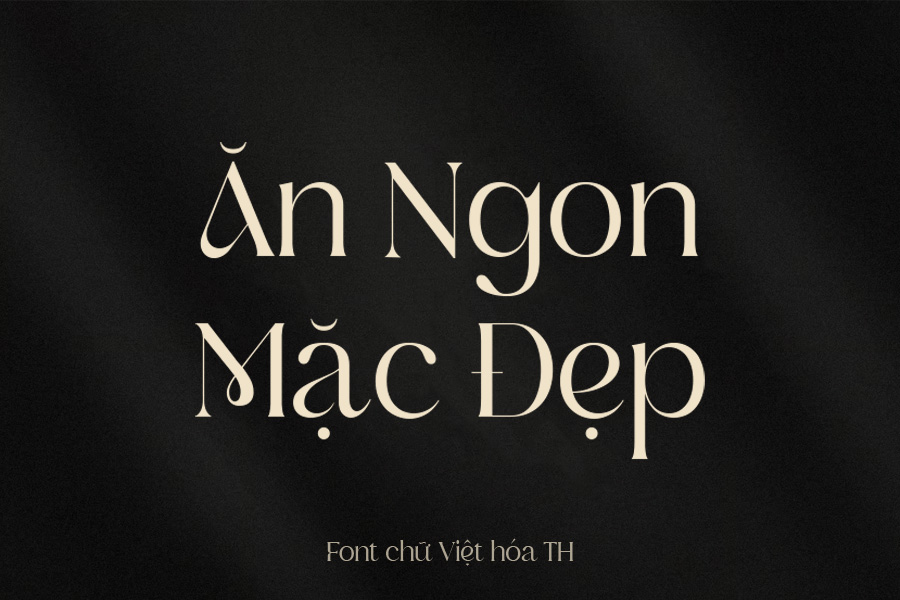
Tải font TH Waking nếu anh đang thiết kế bìa ebook, heading chương và tài liệu tư vấn cao cấp. Điểm mạnh của TH Waking là serif hiện đại, tạo cảm giác đáng tin và có chiều sâu ngay từ trang bìa. Với ebook hoặc lead magnet, font này nên được thử trên cả trang bìa và một trang nội dung mẫu để xem dấu tiếng Việt, khoảng cách dòng và độ rõ của bullet.
Khi dùng trong PDF bán hàng, anh nên xác định vai trò trước: font nào dành cho tiêu đề lớn, font nào dành cho heading phụ, font nào dùng cho đoạn mô tả. Nếu dùng TH Waking cho cover, phần body nên đi với một sans-serif sạch để tài liệu không bị nặng mắt.
2. TH Marlino - ebook chuyên môn, whitepaper, guide dài và báo cáo PDF
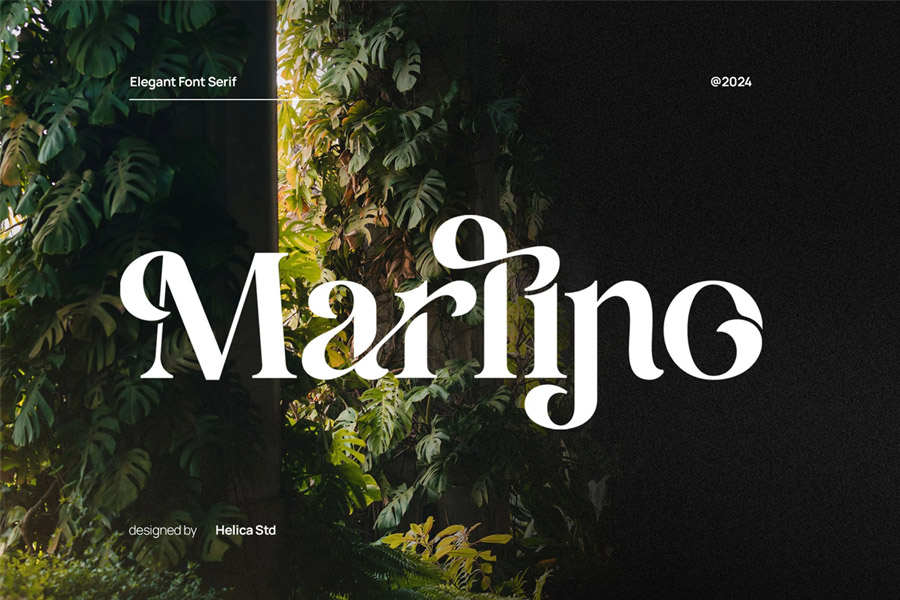
Tải font TH Marlino nếu anh đang thiết kế ebook chuyên môn, whitepaper, guide dài và báo cáo PDF. Điểm mạnh của TH Marlino là chữ có chân rõ ràng, phù hợp với nội dung cần giọng điệu nghiêm túc. Với ebook hoặc lead magnet, font này nên được thử trên cả trang bìa và một trang nội dung mẫu để xem dấu tiếng Việt, khoảng cách dòng và độ rõ của bullet.
Khi dùng trong PDF bán hàng, anh nên xác định vai trò trước: font nào dành cho tiêu đề lớn, font nào dành cho heading phụ, font nào dùng cho đoạn mô tả. Nếu dùng TH Marlino cho cover, phần body nên đi với một sans-serif sạch để tài liệu không bị nặng mắt.
3. TH Runsling - lead magnet cho coach, consultant, beauty, lifestyle và dịch vụ premium
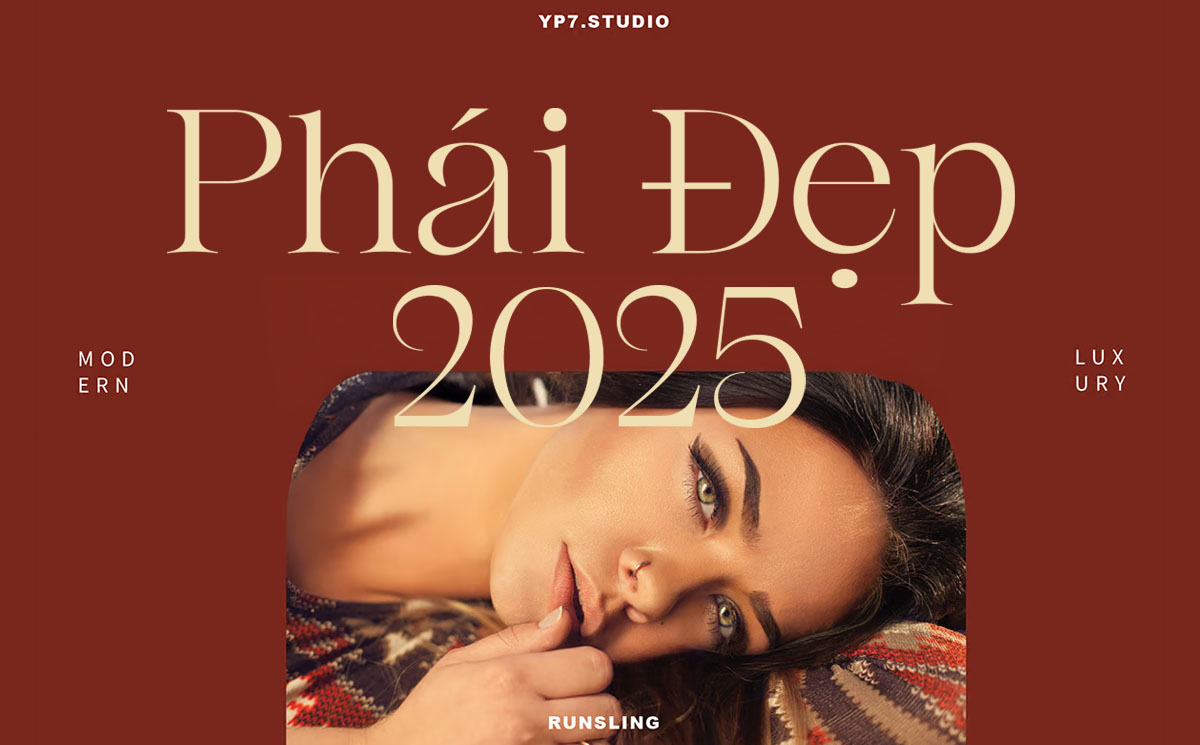
Tải font TH Runsling nếu anh đang thiết kế lead magnet cho coach, consultant, beauty, lifestyle và dịch vụ premium. Điểm mạnh của TH Runsling là thanh lịch, hiện đại, hợp với tài liệu bán hàng không muốn quá cứng. Với ebook hoặc lead magnet, font này nên được thử trên cả trang bìa và một trang nội dung mẫu để xem dấu tiếng Việt, khoảng cách dòng và độ rõ của bullet.
Khi dùng trong PDF bán hàng, anh nên xác định vai trò trước: font nào dành cho tiêu đề lớn, font nào dành cho heading phụ, font nào dùng cho đoạn mô tả. Nếu dùng TH Runsling cho cover, phần body nên đi với một sans-serif sạch để tài liệu không bị nặng mắt.
4. TH Vadola - cover checklist, workbook thẩm mỹ và headline trang mở đầu
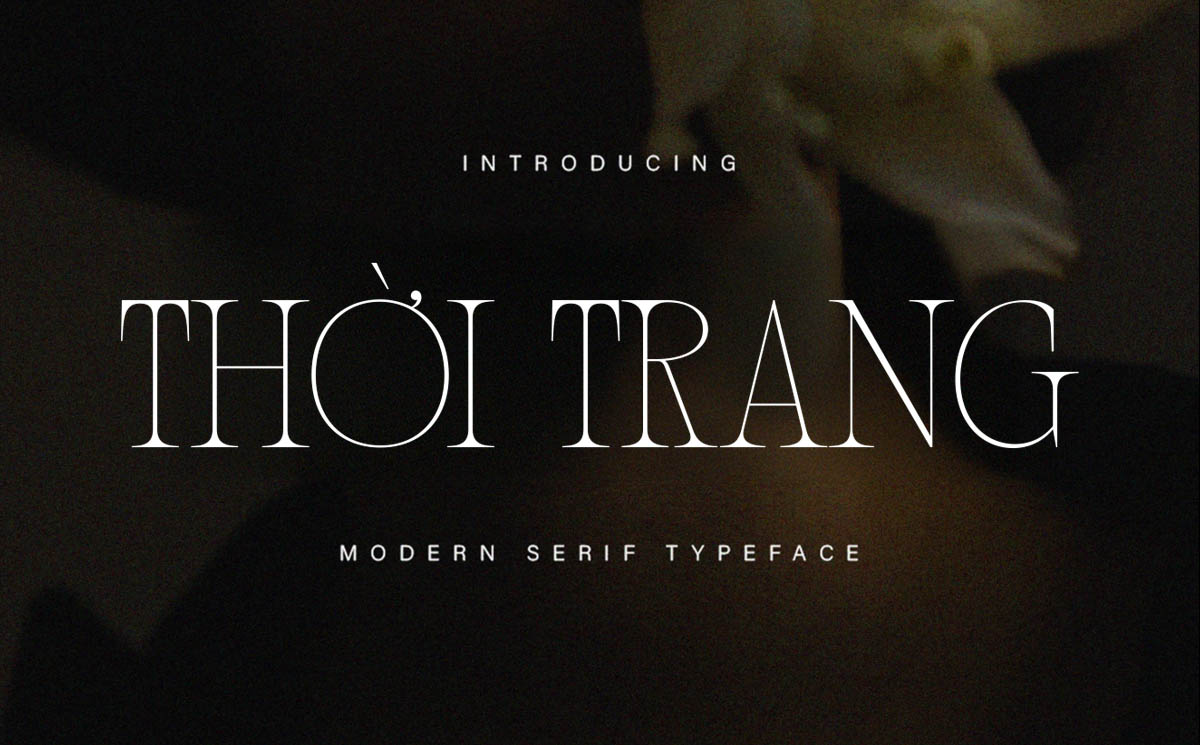
Tải font TH Vadola nếu anh đang thiết kế cover checklist, workbook thẩm mỹ và headline trang mở đầu. Điểm mạnh của TH Vadola là nét mảnh tạo cảm giác nhẹ, tinh tế, đẹp khi đi cùng nhiều khoảng trắng. Với ebook hoặc lead magnet, font này nên được thử trên cả trang bìa và một trang nội dung mẫu để xem dấu tiếng Việt, khoảng cách dòng và độ rõ của bullet.
Khi dùng trong PDF bán hàng, anh nên xác định vai trò trước: font nào dành cho tiêu đề lớn, font nào dành cho heading phụ, font nào dùng cho đoạn mô tả. Nếu dùng TH Vadola cho cover, phần body nên đi với một sans-serif sạch để tài liệu không bị nặng mắt.
5. TH Luxury 2 - ebook thương hiệu cá nhân, tài liệu khóa học và mini guide cao cấp
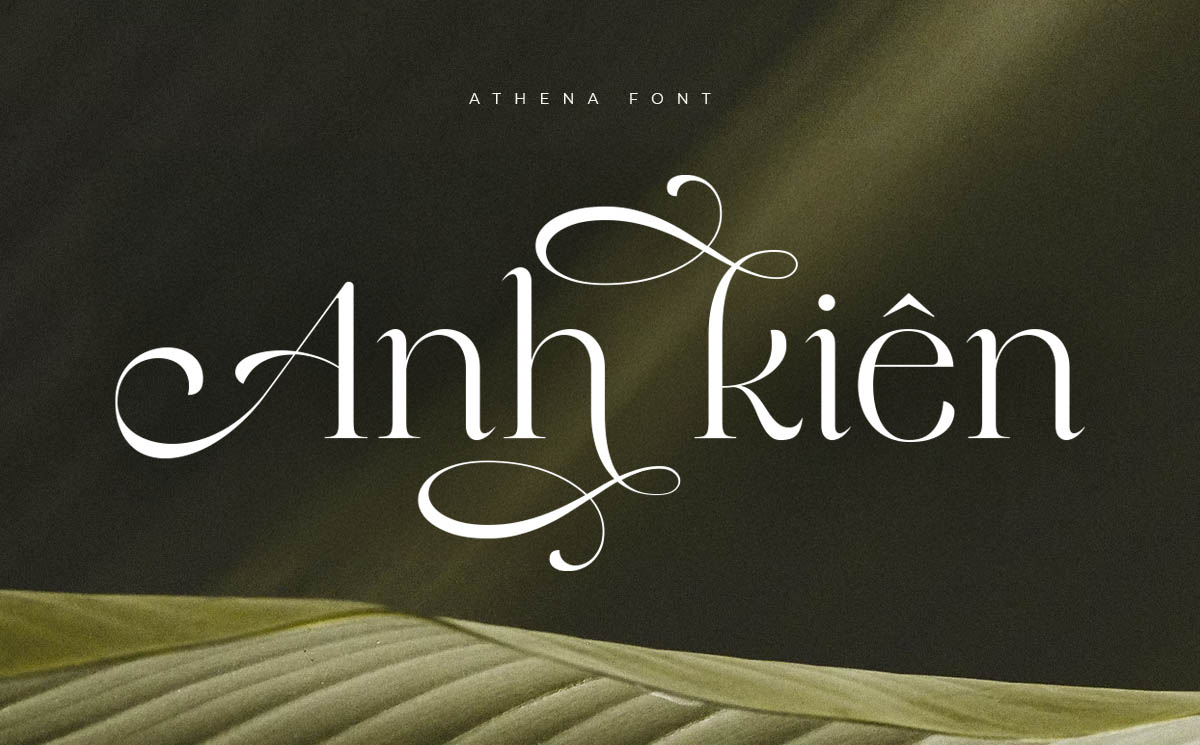
Tải font TH Luxury 2 nếu anh đang thiết kế ebook thương hiệu cá nhân, tài liệu khóa học và mini guide cao cấp. Điểm mạnh của TH Luxury 2 là serif thanh lịch, giúp title nhìn có giá trị hơn khi dùng trên bìa PDF. Với ebook hoặc lead magnet, font này nên được thử trên cả trang bìa và một trang nội dung mẫu để xem dấu tiếng Việt, khoảng cách dòng và độ rõ của bullet.
Khi dùng trong PDF bán hàng, anh nên xác định vai trò trước: font nào dành cho tiêu đề lớn, font nào dành cho heading phụ, font nào dùng cho đoạn mô tả. Nếu dùng TH Luxury 2 cho cover, phần body nên đi với một sans-serif sạch để tài liệu không bị nặng mắt.
6. TH Luxury 5 - lookbook PDF, tài liệu bán hàng ngành làm đẹp, thời trang và dịch vụ
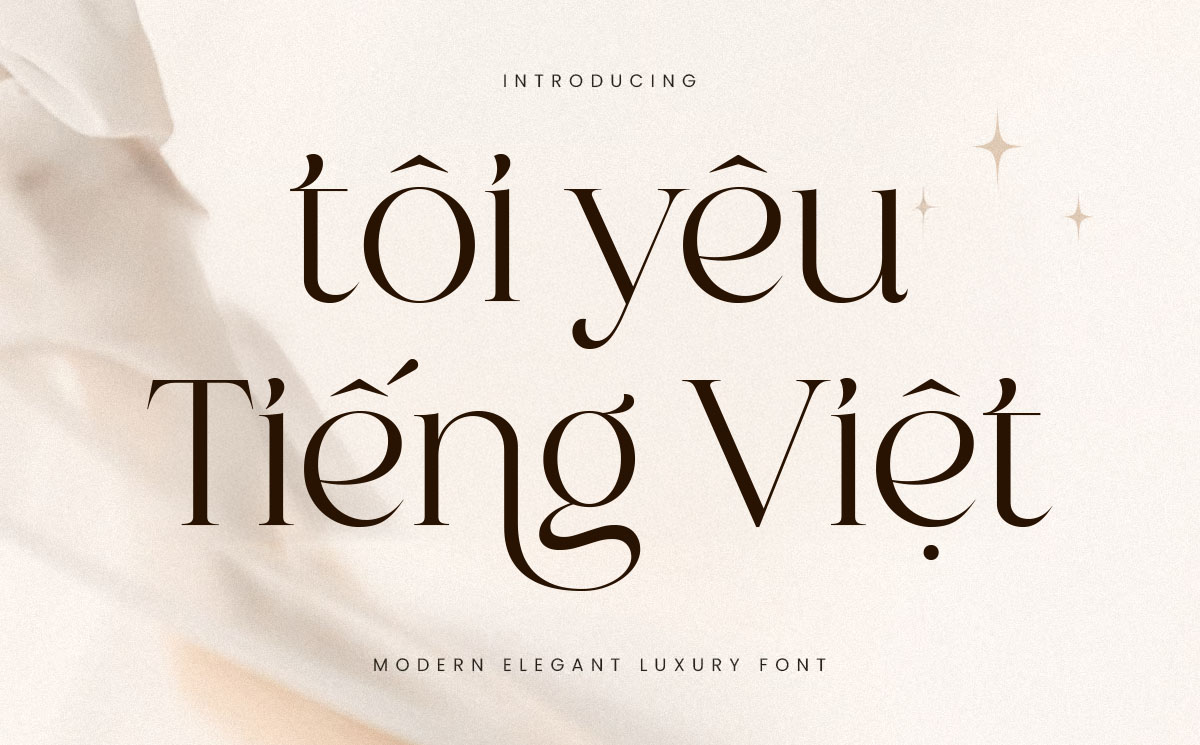
Với 15 font TH Việt hóa trên, anh có thể xây nhiều phong cách PDF khác nhau: chuyên gia, sang trọng, tối giản, giáo dục, bán hàng hoặc lifestyle. Chọn đúng font, giữ hệ thống phân cấp rõ ràng và test kỹ trên mobile là ba bước quan trọng nhất trước khi xuất bản tài liệu.